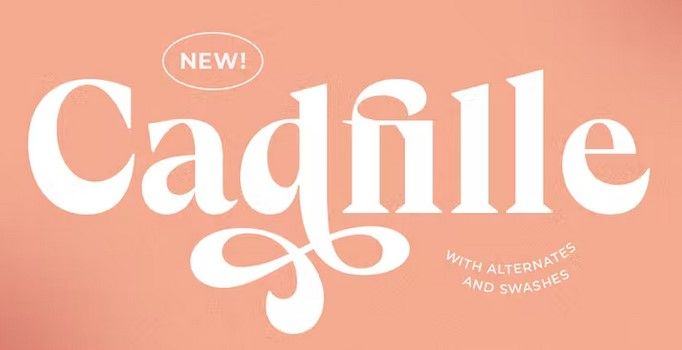
あなたのビジネスのための18のロゴフォント
効果的なロゴは、会社のストーリー、そのビジョンと価値を伝え、フォントはほぼすべてのロゴの基盤です。 結局のところ、ロゴは魅力的なグラフィックデザイン以上のものであり、ビジネスの象徴的な名前、顧客の心の中のブランドの視覚的表現として機能します。 また、ロゴデザインに最適な幾何学的要素を選択する前に、完璧なロゴフォントを決定することが重要です。 しかし、ロゴに最適なフォントは何ですか?
ビジネスロゴフォントの選び方
あなたのビジネスのためのロゴを作る方法を知りたいなら、あなたはおそらくあなたのビジネスのロゴに最適なフォントを選ぶ方法について興味があります。 フォントはロゴ全体のトーンを設定し、他のすべてのデザイン要素に影響を与えます。
AdobeFontsやEnvatoElementsなどの最高のフォントサイトから、ロゴに適したフォントとして何百万ものオプションが利用できます。 最高のロゴフォントをどのように選択しますか? 次のヒントは、中小企業に最適なロゴフォントを選択するのに役立ちます。
あなたのブランドアイデンティティを忘れないでください
会社のロゴは、ブランドのアイデンティティの重要な部分です。 結局のところ、ロゴは顧客の心の中でビジネスとその製品を視覚的に表しています。 したがって、ビジネスロゴフォントを選択する際には、ブランドの個性を考慮することが重要です。 ブランドはクラシックでエレガントですか、それとももっと楽しく冒険的ですか? これらやその他のブランドアイデンティティを表すフォントがあります。
さまざまなフォントファミリを理解する
特定のロゴフォントを選択する前に、ブランドを最もよく表すフォントファミリを決定することにより、オプションを大幅に絞り込むことができます。 セリフまたはサンセリフ書体を含むフォントを選択しますか? おそらく、スクリプトフォントやノベルティレタリングを好むかもしれません。
フォントカテゴリのタイプによって、ロゴフォントに関連する他の多くの影響の中でも、ブランドがセリフまたは楽しいものでフォーマルで洗練されていると見なされ、サンセリフまたはスクリプトでリラックスしていると見なされるかどうかが決まります。
計画されているロゴの使用を検討する
あなたのロゴはどのように使用されますか? ロゴはどこに表示されますか? ロゴは大きな看板に表示されますか、それともモバイルアプリに表示されますか? 一部のフォントは、離れた場所から大きな活字で表示したときに読みやすくなりますが、他のフォントは、細かい部分をより適切に表示できます。 スケーラブルでクリアで、小さいフォーマットと大きいフォーマットの両方で表示できるフォントが必要な場合もあります。
単純にする
効果的なロゴはシンプルなロゴです。 ミニマリストのロゴデザインは、ロゴをデザインする際の重要な品質である読みやすさと認識を支援します。 したがって、ビジネスロゴフォントも、全体的なミニマリストロゴデザインを支援するためにシンプルである必要があります。 ロゴには2つ以下のフォントを使用し、クラシックな線と洗練されていないスタイルのフォントを選択してください。
ビジネスロゴに最適なステンシルフォント
ステンシルフォントには、ストロークにスリットが入った書体が含まれており、カットされたかのように見えます。 ステンシルフォントは、注目を集めて発言するシンプルでありながら太字の文字で構成されています。 さまざまなステンシルフォントが、AdobeやEnvato Elementsなどの人気のあるリソースから入手できます。その中には、中小企業のロゴをデザインするのに理想的なフォントも含まれます。
1.ルフィナステンシル
Adobeやその他のソースからの芸術的なRufinaステンシルフォントは、ステンシルというよりも芸術的なデザインのように見える、シンプルでありながらエレガントな書体です。 Bodoniの影響を受けたステンシルフォントは、スタイルとセンスを表現したいビジネスに最適です。
2.ステンシル
アドビのオリジナルのステンシルフォントは、長年にわたってロゴデザインのために無数のブランドによって選ばれてきました。 大胆な書体は力強い表現であり、その読みやすさは遠くからでもはっきりとわかります。
3.ラストステンシル
Adobeやその他のオンラインソースから入手できるLustStencilフォントは、他のステンシルフォントと同様に大胆でクリアですが、書体はスタイリッシュなセリフを追加して文字にセンスを加えます。 このオプションは、競合他社との差別化を図ろうとしているブランドに最適なロゴフォントです。
ロゴに最適なスクリプトフォント
サンセリフのデジタル化されたキャラクターの海の中で確実に目立つロゴが欲しいですか? スクリプトフォントは、現代の標準とは対照的な視覚的な魅力を提供するため、ロゴフォントとして人気があります。 ブランドのロゴに個性を持たせたい場合は、次のロゴ用スクリプトフォントのいずれかを試してください。
4.ドグマ
Adobeやその他のさまざまなソースで見つかったDogmaフォントは、明快さと読みやすさのために設計されたサンセリフスクリプト書体を特徴としています。 Dogmaスクリプトフォントは、メッセージを明確に伝えながら、ロゴで際立っています。
5. Blenda
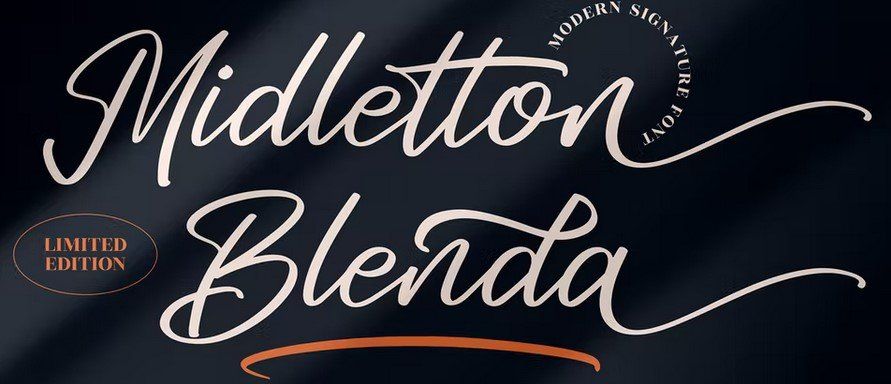
EnvatoElementsから入手できるMiddletonBlendaスクリプトフォントは、洗練された優雅さを備えたロゴを提供するスクリプト書体です。 同時に、フォントは印刷形式とデジタル形式の両方で明確で読みやすいままです。
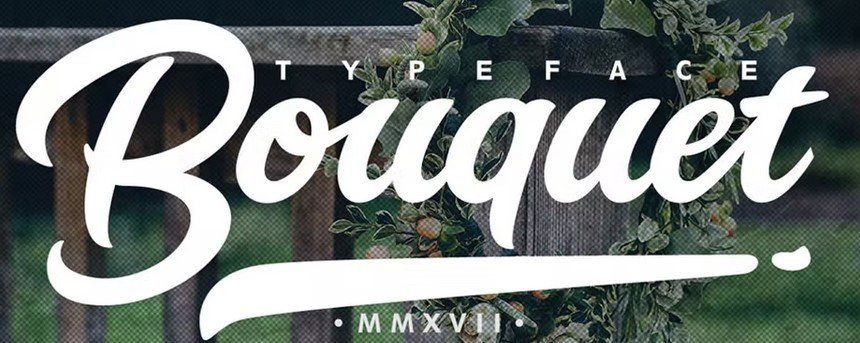
6.ブーケ
スポーティでエキサイティングなBouquet書体は、太い筆記体のレタリングが特徴のスクリプトフォントです。 Envato Elementsやその他のソースから入手できるBouquetフォントは、どのロゴでも読みやすいメッセージで強力なステートメントを作成するはずです。
最高のサンセリフロゴフォント
活版印刷の用語では、サンセリフは、セリフとして知られている、ストロークの終わりに拡張機能を備えていないレタリングを指します。 サンセリフフォントは、読みやすさ、明瞭さ、汎用性から、ロゴデザインの人気のある選択肢です。 何千ものサンセリフ書体から選択できますが、強力なロゴフォントとして次のものを選択できます。
7.ITCアバンギャルドゴシック
Adobe Fontsから入手できる、ITC Avante Garde Gothicフォントのようなゴシック書体は、ロゴにシンプルでクリアなテキストを提供する強力なサンセリフフォントです。 幾何学的なサンセリフフォントは、さまざまなロゴスタイルに一致するように複数の重みで利用できます。
8.Sansを開きます
アドビから入手できるもう1つの人気のあるサンセリフ書体は、2011年にGoogleから委託されたヒューマニストのサンセリフフォントであるOpen Sansフォントです。OpenSansは、印刷形式とWeb形式の両方で明確で強力なメッセージを提供するため、優れたロゴフォントです。
9.フューチュラ
Futuraは、ディスプレイやロゴフォントに人気のあるサンセリフ書体です。 Adobe Fontsや他の多くのソースから提供されている、Futuraの幾何学的なデザインは、強力なロゴの基盤として人気があります。
10.アクメゴシック
注目を集める印象的なロゴフォントが欲しいですか? Acme Gothicフォントは、昨年の厚くて薄いゴシック文字のスタイルに似せて設計されており、明瞭さと読みやすさを維持しながら、強力なメッセージを伝えます。
11.アクシア
Axiaは、10種類の幅のユニ幅のサンセリフ文字を備えた用途の広いフォントファミリで、それぞれ小文字と斜体の両方で使用できます。 アドビやその他のプラットフォームから利用できるAxiaのさまざまなオプションにより、ブランド名から追加の詳細まで、さまざまなロゴの用途でフォントを紹介できます。
最高のスラブセリフロゴフォント
スクエアセリフまたはエジプトスタイルとしても知られるスラブセリフ書体は、厚いブロックのようなセリフのおかげで、ゴシック文字のシンプルさを備えた洗練されたセリフを提供するため、ロゴに人気があります。 スラブセリフのロゴフォントの品揃えは、AdobeFontsやEnvataElementsなどのソースから入手できます。
12.ビスタスラブセリフ
Vista Slab Serifは、その明瞭さと読みやすさで人気のあるモダンなロゴフォントです。 書体はAdobeやその他のソースからさまざまな太さで入手できるため、あらゆる種類のロゴデザインに対応できます。
13.ロゾースラブ
特定のスラブセリフファミリーは非常に明確で大胆であるため、ロゴデザイン用に作成する必要がありました。 EnvatoElementsやその他のオンラインリソースで提供されているRoseauSlabは、そのプレゼンテーションにおいてモダンでミニマリストであり、そのさまざまな重みにより、ロゴフォントの多様な選択肢となっています。
ロゴ用のより良いフォント
最高のロゴフォントのいくつかは、上記のカテゴリに含まれません。 中小企業の所有者は、独自のプレゼンテーションのために斬新なフォントで会社をブランド化することを選択するかもしれません。あるいは、優雅さと洗練さを加えるために、より伝統的なセリフフォントを選択するかもしれません。
14.ガラモンドプレミア
ガラモンドは、読みやすさと優雅さ、そしてクリアで鮮明なセリフにより人気のあるディスプレイフォントです。 アドビのオリジナルのGaramondPremierフォントは、ロゴの書体に最適であり、洗練された感覚で直接メッセージを配信することができます。
15.トラヤヌス
さまざまなトーンや意味を伝えるために、多くのクールなロゴフォントが用意されています。 AdobeのTrajanフォントは、古典的なローマ字に基づいたセリフ書体です。 クリップスと明確なレタリングは、ロゴフォントの中でお気に入りの選択肢になります。
16.ヴェローナ
洗練されたセンスを保ちながら、あなたのロゴで声明を出したいですか? Envato Elementsやその他のソースが提供する書体であるVeronaフォントは、クリアな文字とエレガントなスクリプトのようなストロークを備えたエレガントな表示フォントです。
17. Munale Loird
Munale Loidセリフ表示フォントは、ミニマリストデザインでシックなトーンを提供します。 Envato Elementsやその他のソースから入手できる書体であるスタイリッシュなフォントは、新鮮で読みやすいロゴデザインを作成します。
18. Cadfille
個性あふれるロゴをデザインしてみませんか? Cadfilleは、大胆でモダンなセリフと呼ばれ、ロゴ、見出し、その他の大胆なディスプレイの愛らしい書体になっています。 最新のフォントは、EnvatoElementsやその他のさまざまなフォントリソースから入手できます。
• アディダスの有名なロゴは、サンセリフ書体であるAvant Gard Gothic demiフォントに基づいて構築されており、ブランド認知度がすぐに向上します。
• Twitterのすぐに認識できるロゴ機能は、 Pico書体で示されているブランド名です。これは、大小のフォーマットで読みやすい、クリアでありながら楽しいロゴフォントです。
• 世界的に有名なFacebookのロゴは、クラシックなKlavika Boldフォントを特徴としており、現在は同社の代名詞となっているビジュアルブランドを作成しています。
• ジレットの認識可能なロゴは、印刷およびオンライン形式で際立つ余分な黒の色合いのFuturaフォントに依存しています。
• 驚いたことに、有名なEnergizerロゴは、最もクラシックで人気のあるロゴフォントの1つであるHelveticaを使用して作成されました。
• その有名なiTunesロゴやその他の人気のあるロゴについて、Appleは最高のロゴフォントの1つであるMyriadBoldに依存していました。